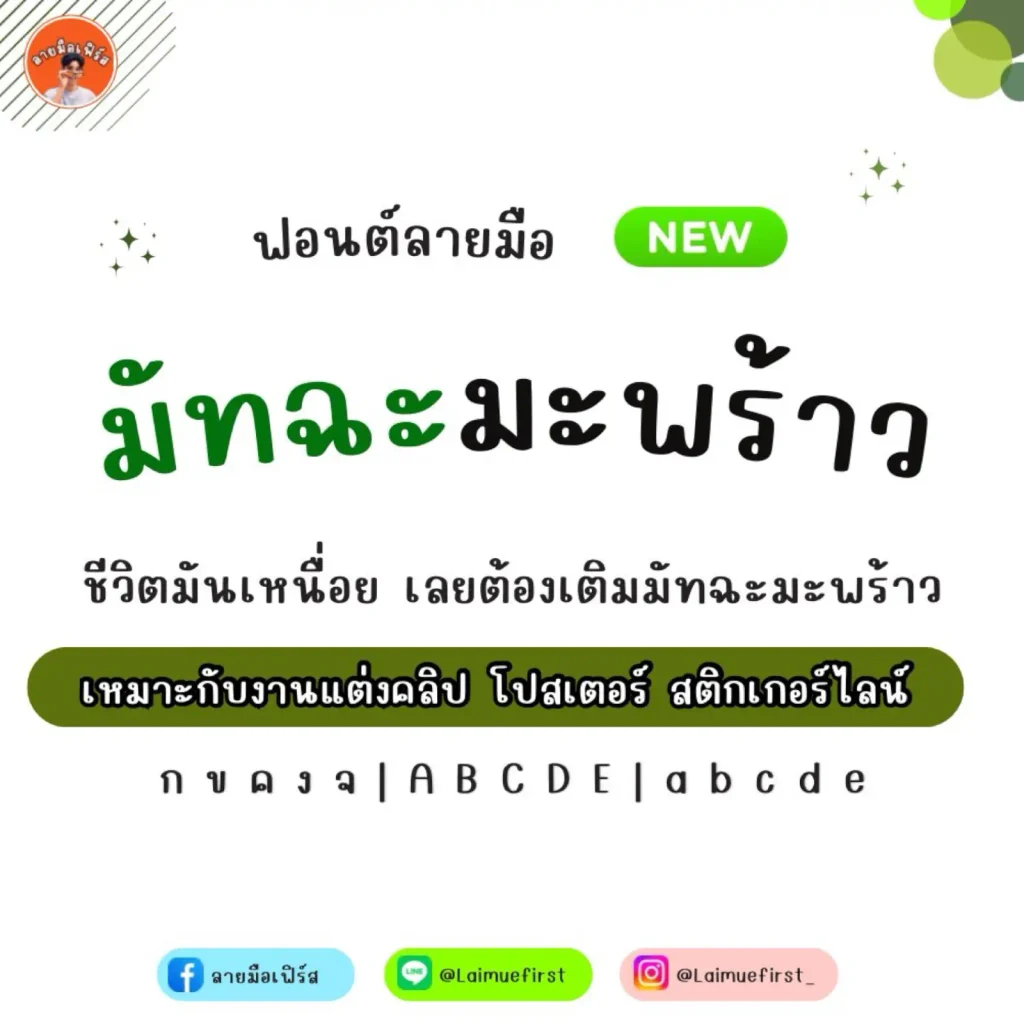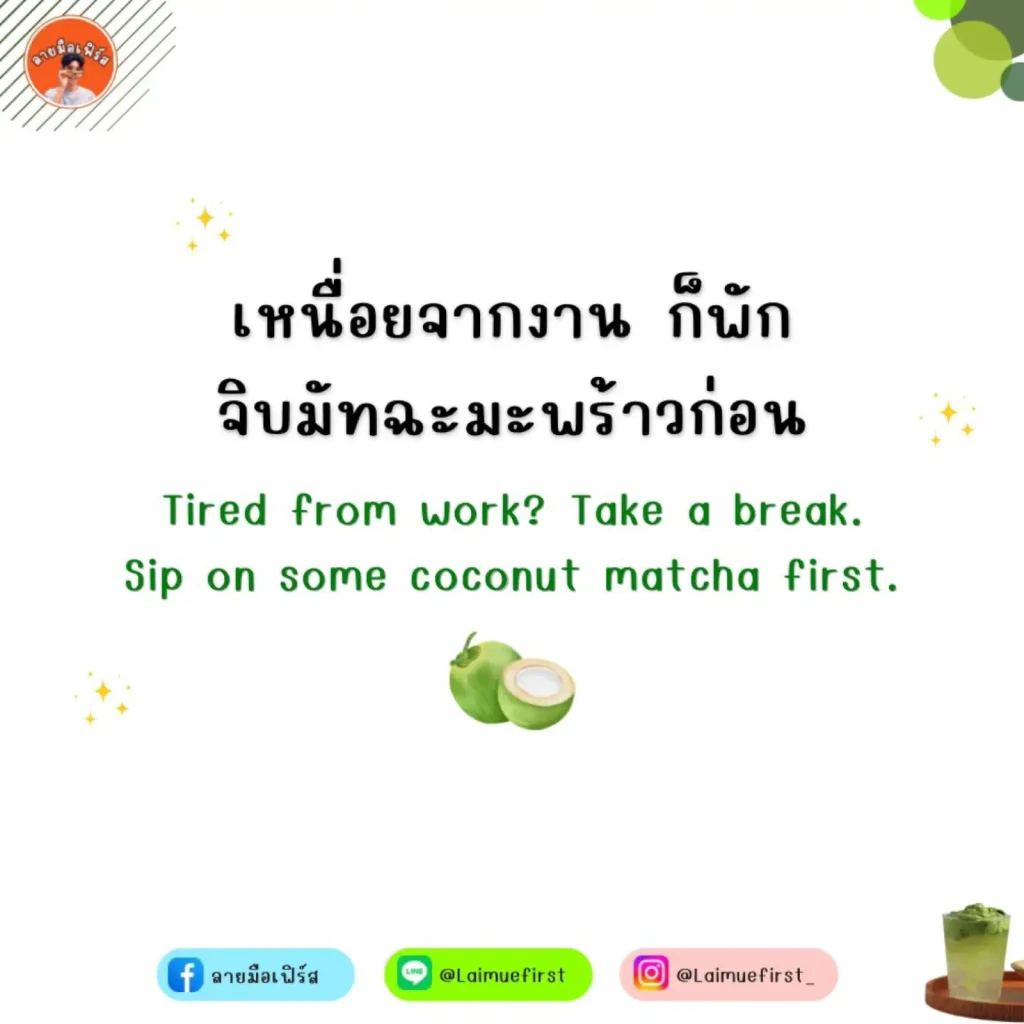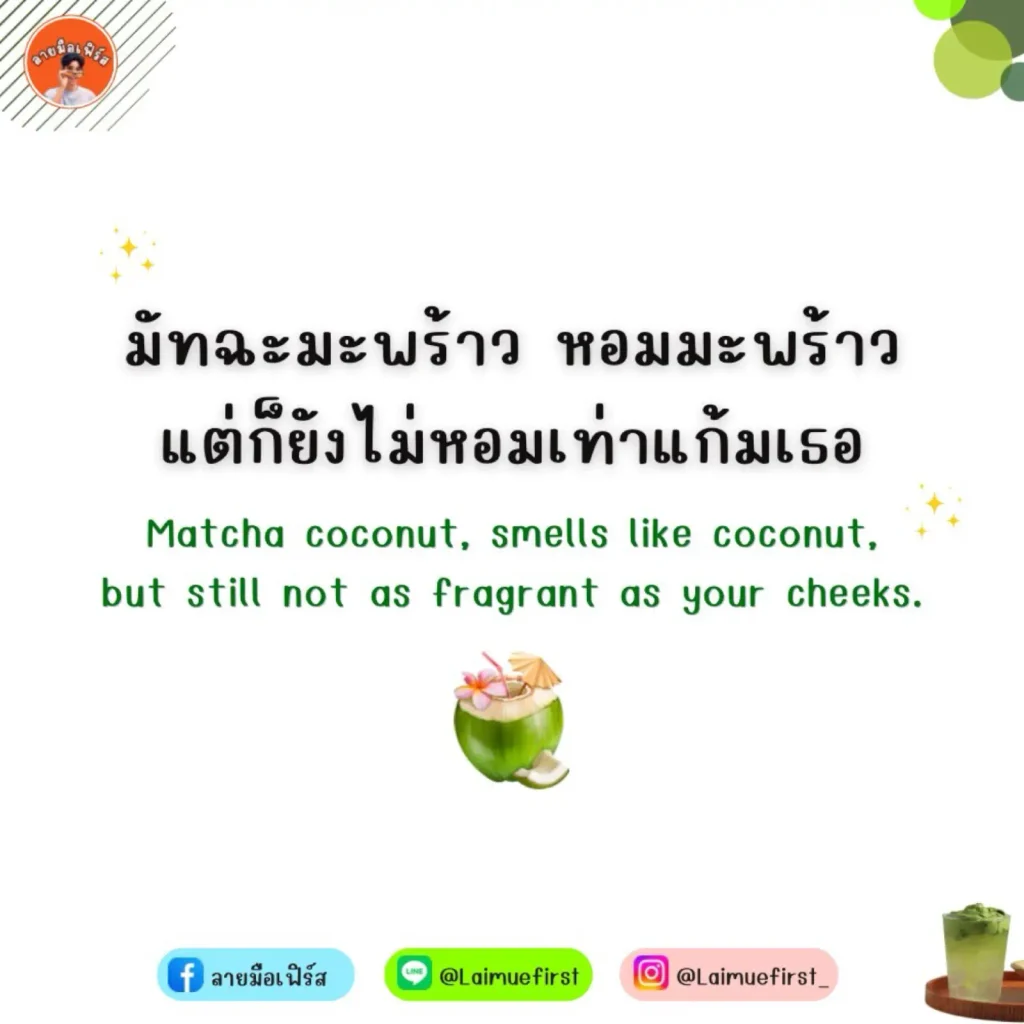
ฟอนต์ลายมือ มัทฉะมะพร้าว (LMF MatchaMaphrao) – แจกฟรีสำหรับทดลองใช้งานแบบส่วนตัวเท่านั้น
- ตัวหนังสือปกติ ไม่มีตัวโปร่งปน
มัทฉะมะพร้าว (LMF MatchaMaphrao)